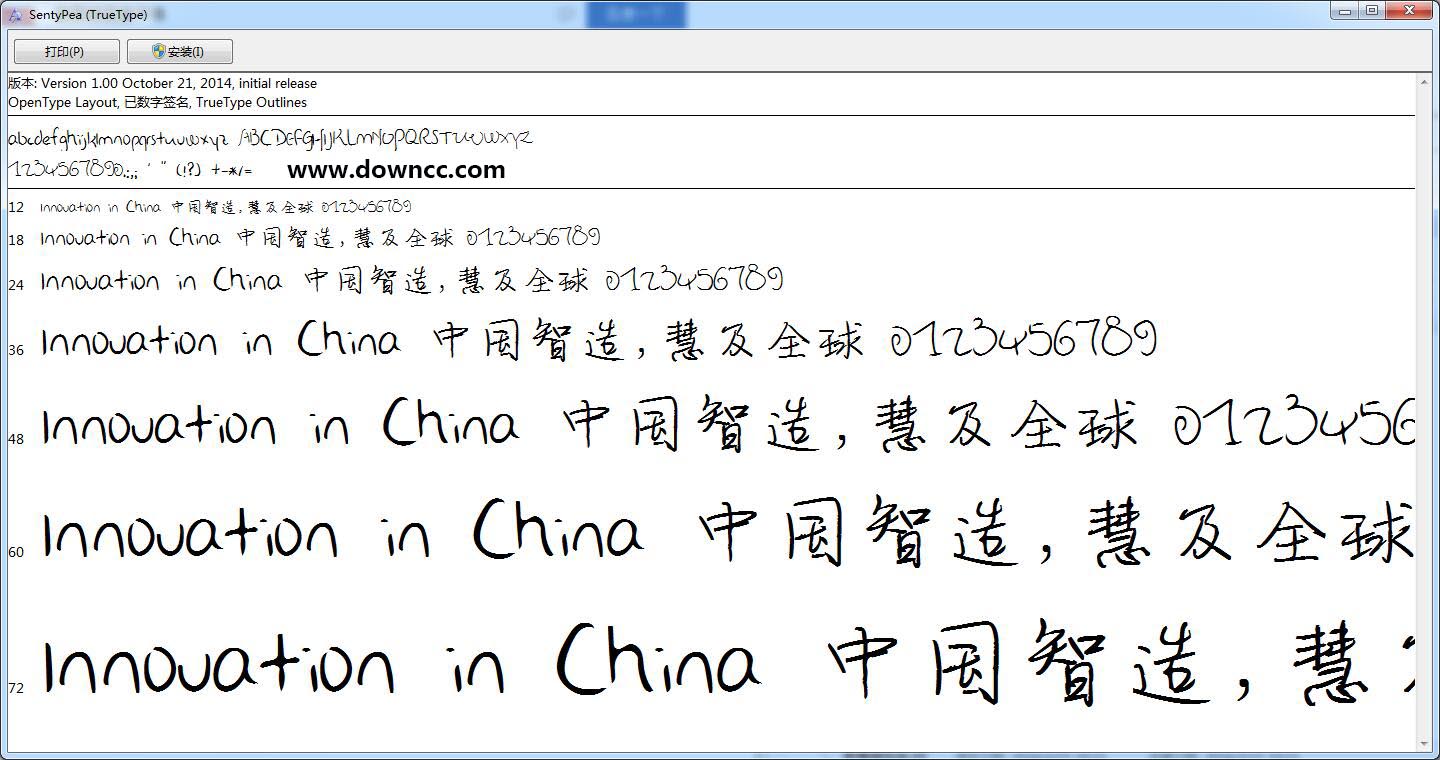
新蒂綠豆體是由新蒂字體庫(kù)推出的字體應(yīng)用。這款字體里面包含了常用簡(jiǎn)體、繁體漢字拉丁字母、數(shù)字,可以在照片上編輯文字信息,進(jìn)行網(wǎng)頁(yè)設(shè)計(jì)等等。文字看起來(lái)活波隨性,比較大氣!歡迎用戶在綠色資源網(wǎng)下載!
新蒂綠豆體是一款手寫(xiě)風(fēng)格的字體,這款字體為用戶提供了中英文雙語(yǔ)字體,用于廣告設(shè)計(jì)、網(wǎng)頁(yè)設(shè)計(jì)、包裝設(shè)計(jì)等方面!操作簡(jiǎn)單,下載后解壓安裝即可使用!